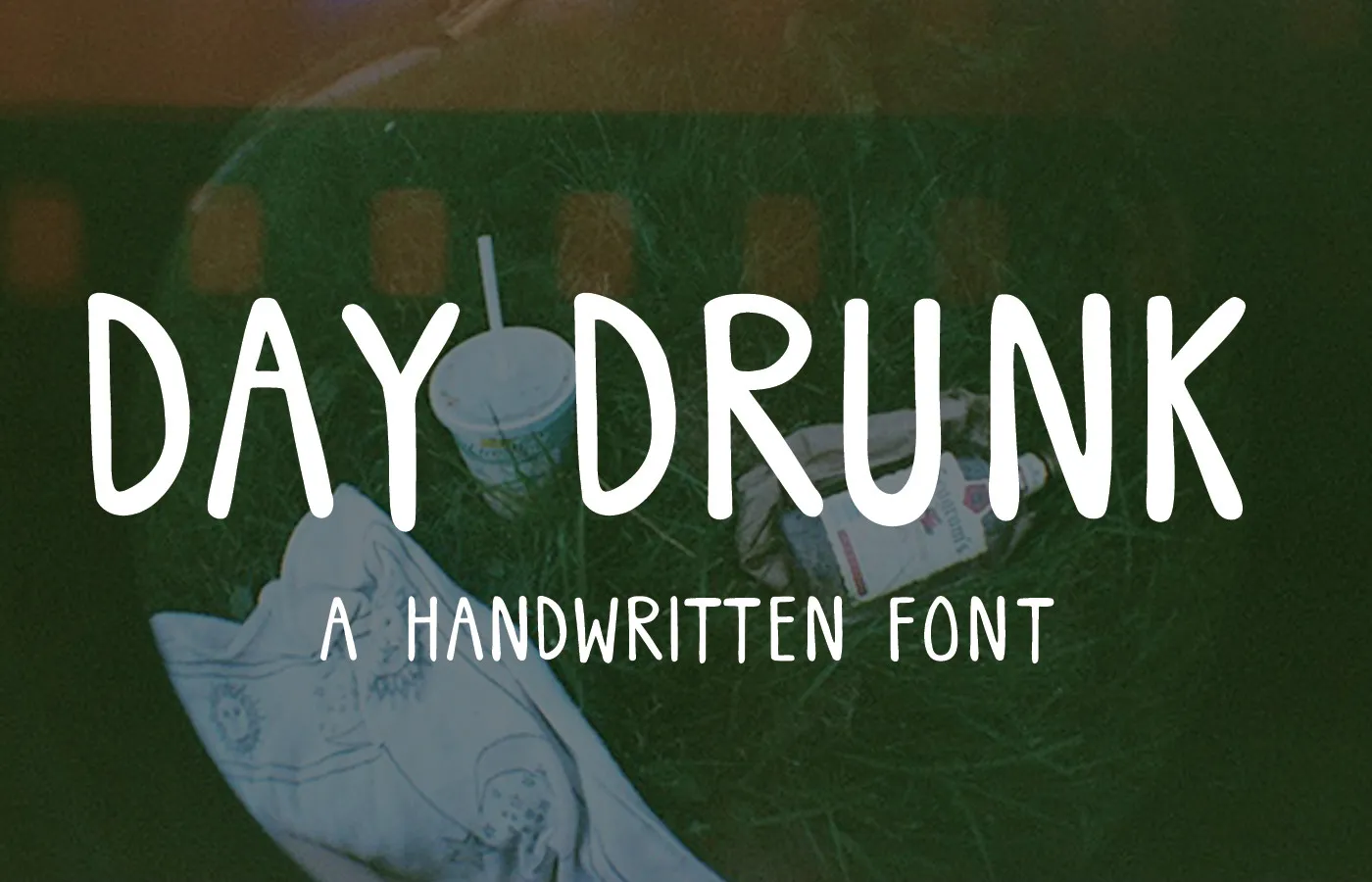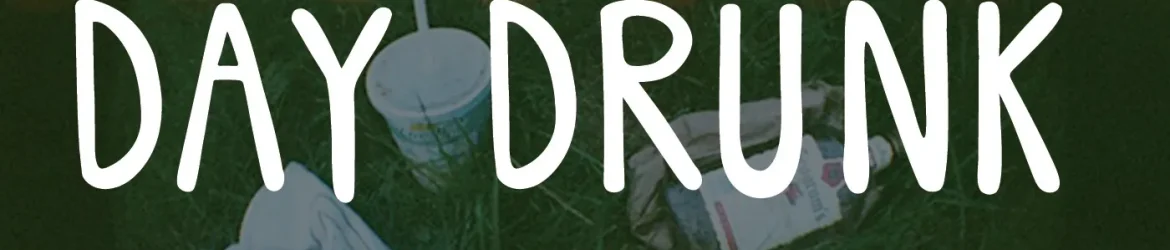
Day Drunk Font – Download Grátis
A ‘Day Drunk Font’ é uma elegante escolha para os amantes de escrita livre, ideal para adicionar personalidade aos seus projetos digitais. Desenhada pelo designer Hamilton, essa fonte escrita a mão oferece um toque único e vibrante, perfeitamente adaptável à diversidade dos projetos gráficos que você pode estar desenvolvendo. Suas linhas fluidas e traços expressivos fornecem uma maneira divertida de dar um tom descontraído e inspirador a qualquer projeto. Seja para criar texturas personalizadas, adicionar tags distintivas ou decorar suas postagens no blog com um toque único — a ‘Day Drunk Font’ é certamente o elemento que você precisa para manter seu design inovador e atualizado em uma categoria de fontes escrita a mão vibrante.